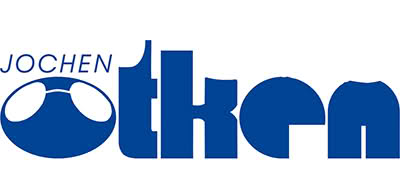
Optiker Schrift gesucht
wisst ihr welche Schrift das ist?
Das Logo ist schon über 20 Jahre alt.
Da hat Pac-Man wohl schon an den Konsonanten geknabbert.
Nee, das sind die besonderen Merkmale der fetten Otken.
du warst wohl schon stolz, den namen überhaupt lesen zu können. leider heißt der typ ötken.
ah, geh. ich habe darauf hingewiesen, dass der gag (fette otken) dadurch etwas hinkt, dass der schriftzug ›ötken‹ lauten soll, und dass der schriftzug dadurch etwas hinkt, dass die buchstabenformen ziemlich ›kreativ‹ sind. ich habe jedenfalls eine weile gerätselt.
Tatsächlich.
Der Mensch heisst Ötken.
Hätte man nun aus dem O von Optiker
und dem Ö von Ötken ne Brille gebastelt,
wärs ein Logo geworden.
Den restlichen Text aus "Sonstwas" und wir hätten uns die ganze Diskussion sparen können.
Der Optiker? Ich denke, der heißt Schrift? Der TE hat doch geschrieben, daß er den Optiker Schrift sucht. Lest Euch doch erst nochmal den Titel des Threads durch, ehe Ihr hier irgendwelche Betrachtungen zur Typographie anstellt, nach denen gar niemand gefragt hat.
Leider nicht, liebe Tine. Mein Selbstschutz sagt mir auch: Das will ich gar nicht. Wenn du die Chance hast, an des Herrn Optikers Logo etwas zu tun, dann empfehle ich, den Reset-Button zu drücken und diese 20-jährige Grausamkeit aus der Welt zu schaffen. Fakt ist, dass kein Mensch das Logo weder mit noch ohne Brille richtig lesen kann (Otken? Ötken?). Vielleicht lässt sich er sich ja zu einem Neu-Design überreden (wobei jede Änderung eine Verbesserung gleichkäme, schlimmer geht es nicht [ok, Glassbuttons mal ausgenommen, aber die sind ja auch mein ™]).